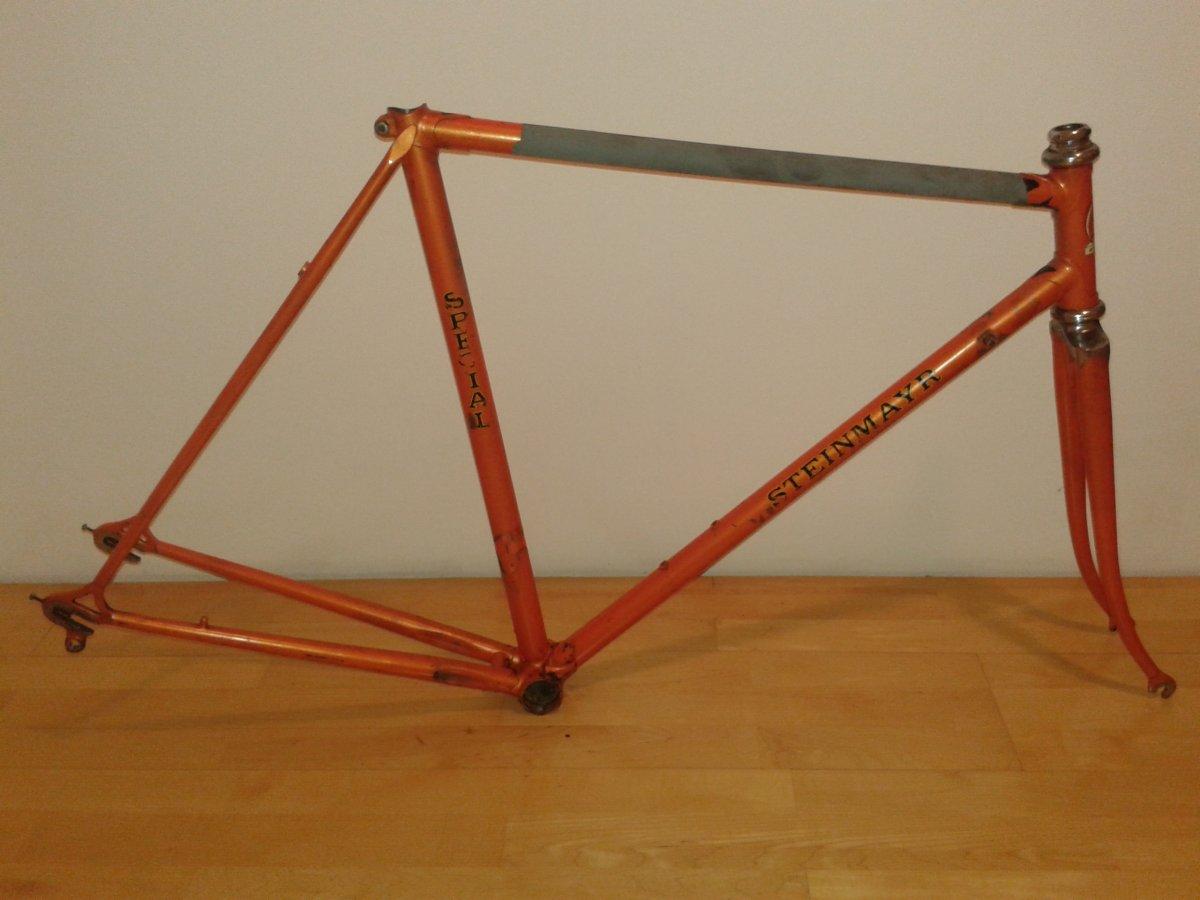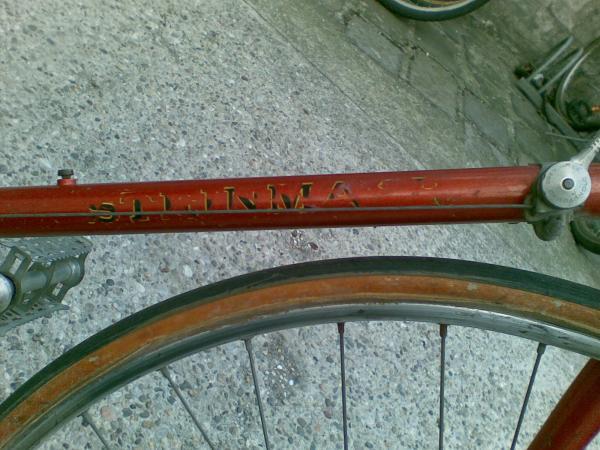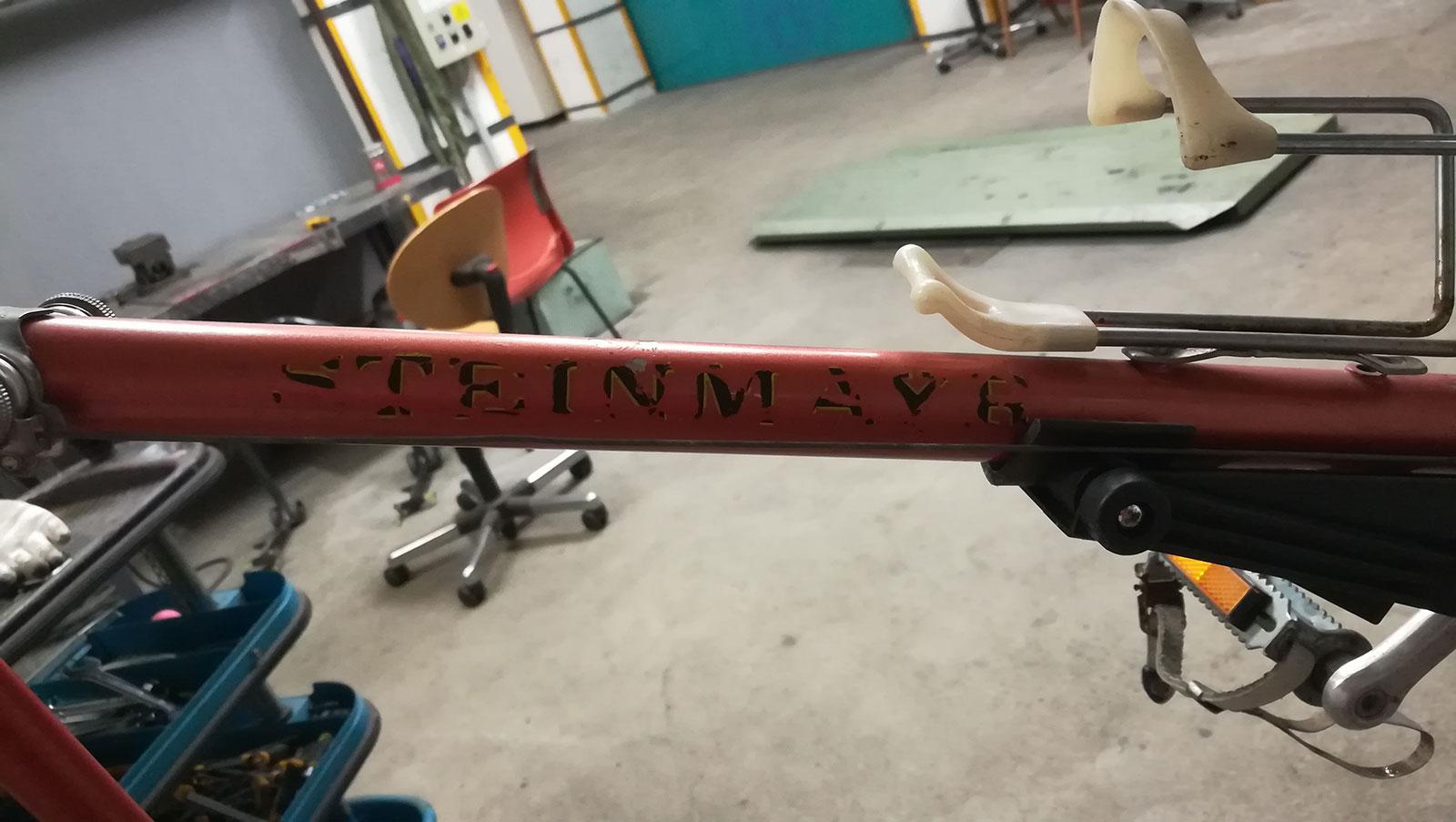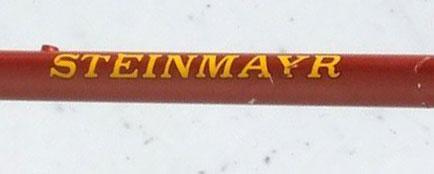
STEINMAYR: Slab-Serifenschriftzug vom Fahrradrahmen
ein Freund von mir hat ein Fahrrad des ehemaligen, österreichischen Rennradprofis Wolfgang Steinmayr ersteigert. Das Rad dürfte von Anfang der 1970er-Jahre stammen, also noch weit weg von digitaler Beschriftung.
Der Schriftzug »STEINMAYR« darauf ist schon ganz schön mitgenommen. Er möchte den natürlich nachbauen und fragt mich, ob ich die Schrift kenne. Naja, sie hat etwas von der Clarendon, aber die eher dreieckige Mittelserife des »E« sowie die Form des »R« spricht m. E. dagegen. Weiß jemand, der vordigitale Musterbücher hat, ob es diese Schrift (zumindest als Vorlage) gegeben hat (was ich eigentlich vermute)?
Das erste Bild ist der ersteigerte Rahmen, die restlichen Bilder (mit den gelben Schriftzügen) sind ähnliche Steinmayr-Rahmen aus dem Google-Recherche-Fundus, die ich grade eben noch zugesandt bekommen habe.
Hmm, schwer. Ich hätte auch auf eine Clarendon Extended getippt abre DU hast recht die sieht anders aus. Sieht man auch gut am R.
Evtl. stand die Schrift Pate und wurde abgemalt, in den 70ern wurde ja vieles noch zusammengebastelt.
Ich würde versuchen soviel wie möglich an Vorlagen von dem Schriftzug zu sammeln und die Schrift dann nachzeichnen. Dazu könnte man evtl. in diversen Rennradforen nach einem Steinmayerbesitzer fragen und ihn bitten den Schriftzug in hoher Auflösung zu fotografieren.